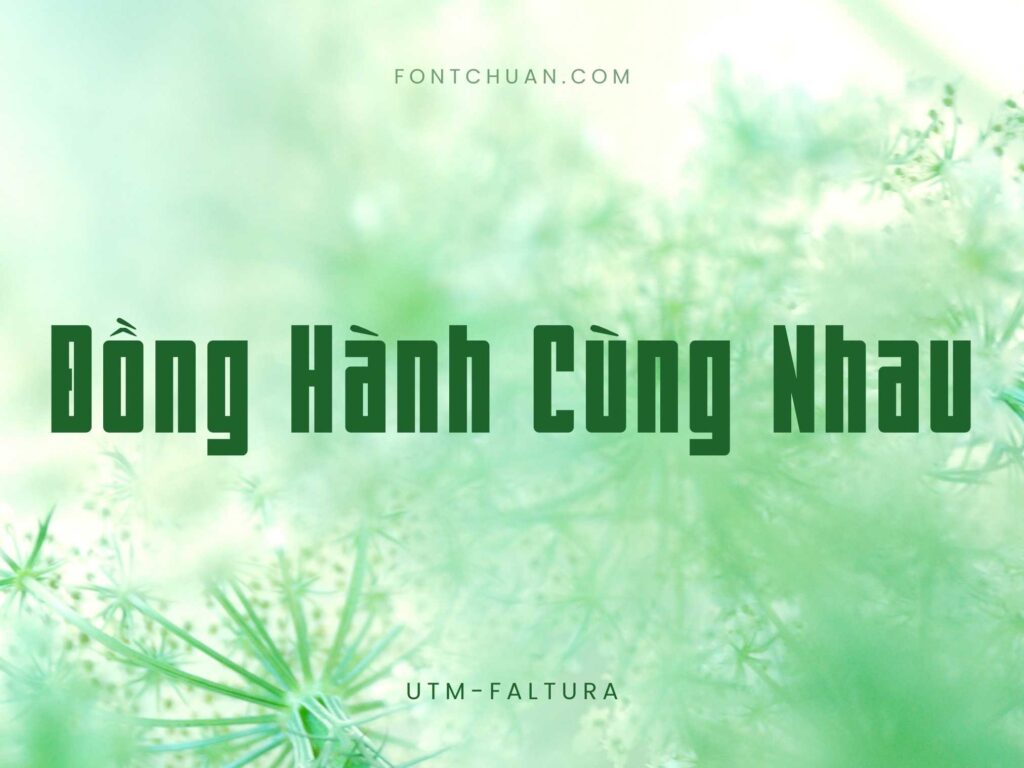
Font UTM Faltura Việt Hóa là một kiểu chữ sans-serif hiện đại, mang phong cách tối giản nhưng vẫn đầy cá tính. Với đường nét gọn gàng, độ dày đồng đều và tính ứng dụng cao, font này là lựa chọn lý tưởng cho các thiết kế đòi hỏi sự chuyên nghiệp, sáng tạo và dễ đọc.